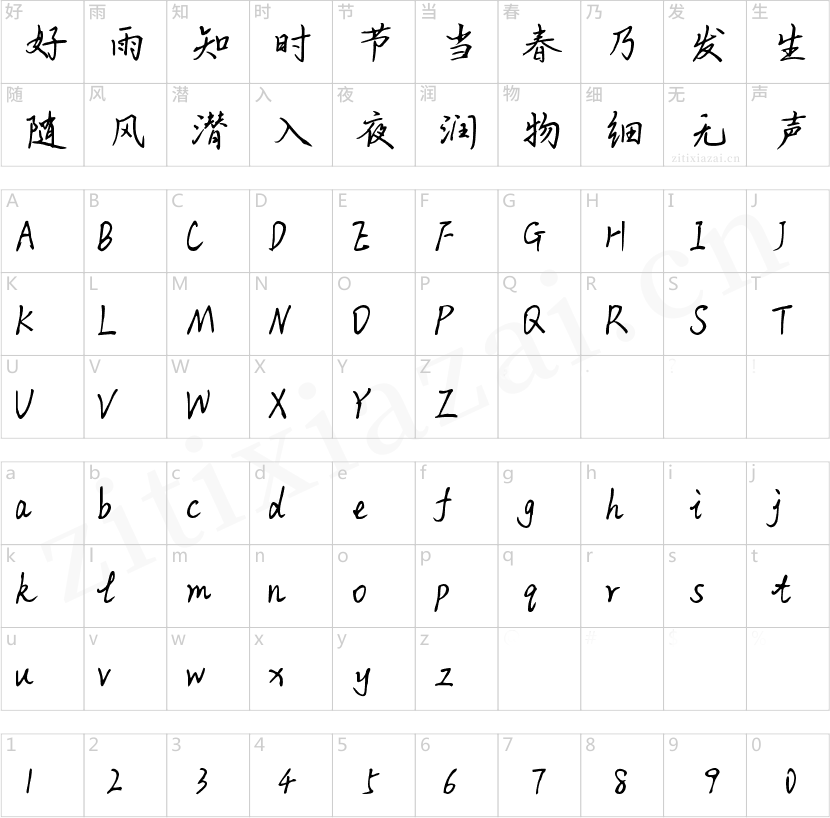
Aa爱在星光里
Aa爱在星光里字体
Aa爱在星光里是一款非常具有艺术性的字体,它的设计灵感来源于对古典艺术的研究,同时又融入了现代字体设计的元素。字形优美,笔画粗细变化自然,给人以大气、典雅的感觉。Aa爱在星光里是一款既传统又现代的字体,它的设计充满艺术感,美观大方,实用性也非常强。无论是对于设计师还是对于普通读者来说,都是一种非常不错的字体选择。Aa爱在星光里适合用于具有艺术感的场合,比如海报、宣传单张、书籍封面等。由于其字形流畅且具有动态感,也适合用于大量的文本排版,如报纸、杂志等。